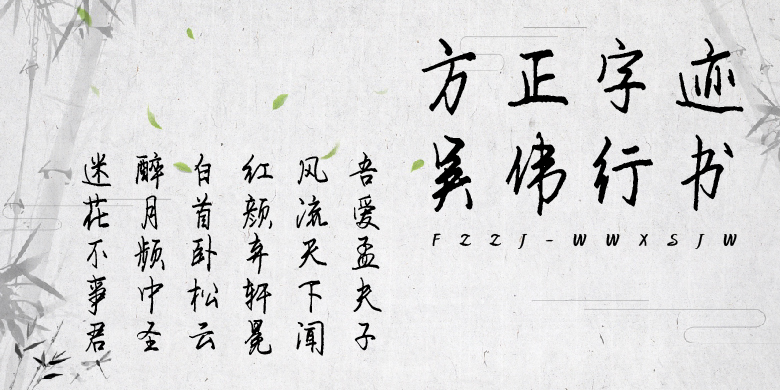
方正字迹-吴伟行书
方正字迹-吴伟行书,这款字体结构工整、笔画清晰,兼顾美观与易读性,适用于标题、正文、海报、包装、LOGO 等多种场景。字形优雅稳定,风格百搭耐看,适配日常排版与创意设计,让文字呈现更舒适、更具质感。方正字迹-吴伟行书一笔一画,皆是细节,以均衡的比例、流畅的线条打造舒适视觉体验,字形端正大气,风格简约现代。无论是商业设计、品牌宣传还是日常排版,都能轻松驾驭,让文字更有格调与力量。方正字迹-吴伟行书字体下载。
方正字迹-吴伟行书,书风刚劲稳健,运笔自然,舒展大方。适用于文化类的宣传设计及各种文书类的写作。
作者吴伟,自幼爱好书法,从军后由于工作的需要,更是与书法结下不解之缘,半生军旅以书为乐,业余时间笔耕不辍。传统书法主攻行书,软硬笔兼备,书风刚劲稳健,运笔流畅自然,字体舒展大方,集众家之长自成一体,擅长行草章法的创作。